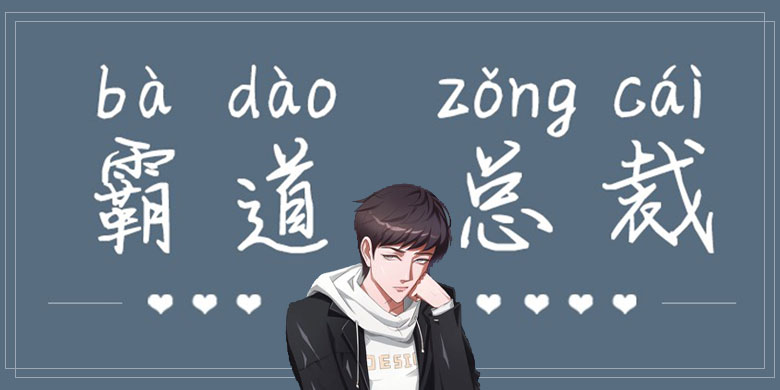
方正手迹-霸道总裁字体说明方正手迹-霸道总裁字体英文名称:FZSJ-BADZC.TTF方正手迹-霸道总裁品牌:方正手迹 设计师: 余丹发行时间:2019字库编码: 大陆简体(GB2312-80)分类: 创意书写字体属性: 心动字字体介绍这是一款拼音字体,它有着硬笔书法字的特点,笔触粗放苍劲不失潇洒,个性手写的灵动和英气体现得淋漓尽致,无论是文艺主标题还是正文书写均是很养眼的。适用于文艺类的书刊、品牌广告和产品包装设计,以及社交网络的个性化用字。字体下载地址官网下载 发布日期 2020年7月20日 发布于 方正字体 标签 GB2312-80, pop, 书法, 方正, 方正手迹, 简体, 粗 上篇文章: 方正手迹-潮范小鲜肉 下篇文章: 方正手迹-几何几何 发表回复 取消回复要发表评论,您必须先登录。